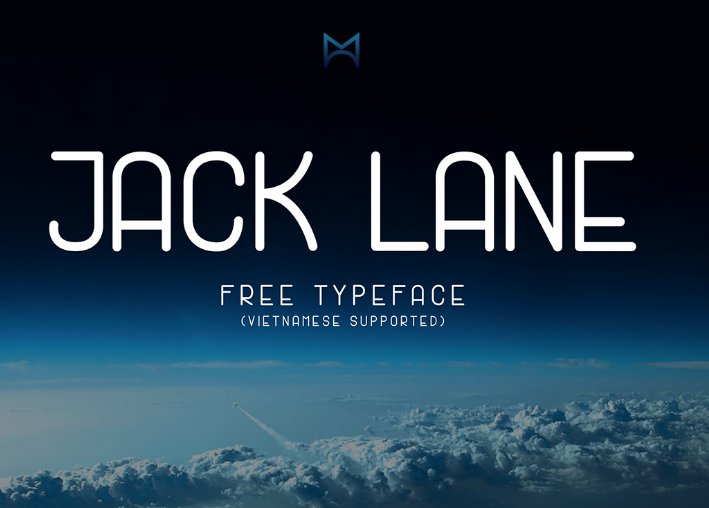
Introduzimos a você uma nova opção no mundo dos tipos gerais, a Jack Lane Typeface criada pelo Mack Trinh. Esta fonte está projetada para se destacar nos ambientes modernos e limpos de design, como logos, headlines e banners. Ela é perfeita para quem busca uma aparência clássica com espaçamento entre as letras estendido em todas as letras maiúsculas, ou simplesmente para uso puramente funcional em letras maiúsculas e minúsculas. A Jack Lane Typeface também tem um estilo elegante quando usada apenas no formato de letras maiúsculas, uma vez que o espaçamento entre elas é amplo. É essa combinação de sofisticação e simplicidade que a torna perfeita para diferentes aplicações gráficas. Perfeito tanto para design de logotipos quanto para layouts de banners, a Jack Lane Typeface oferece uma solução versátil para criações modernas e elegantes. Sempre pronto para dar um toque único em qualquer projeto visual que você possa ter.